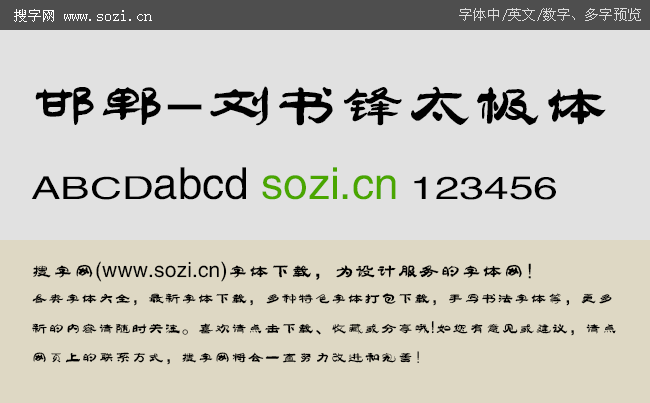
邯鄲-劉書鋒太極體
搜字網(wǎng)提供一款邯鄲-劉書鋒太極體中文書法字體下載,劉書鋒太極體吸取了太極剛?cè)岵木A,將舒展優(yōu)美、動作和順、平正樸實的太極文化融入書法當(dāng)中,寫出來的字張弛有度、柔中帶剛,又灑脫不羈、隨心所欲。適用于畫冊設(shè)計,海報設(shè)計,圖書印刷等廣告設(shè)計場合使用。